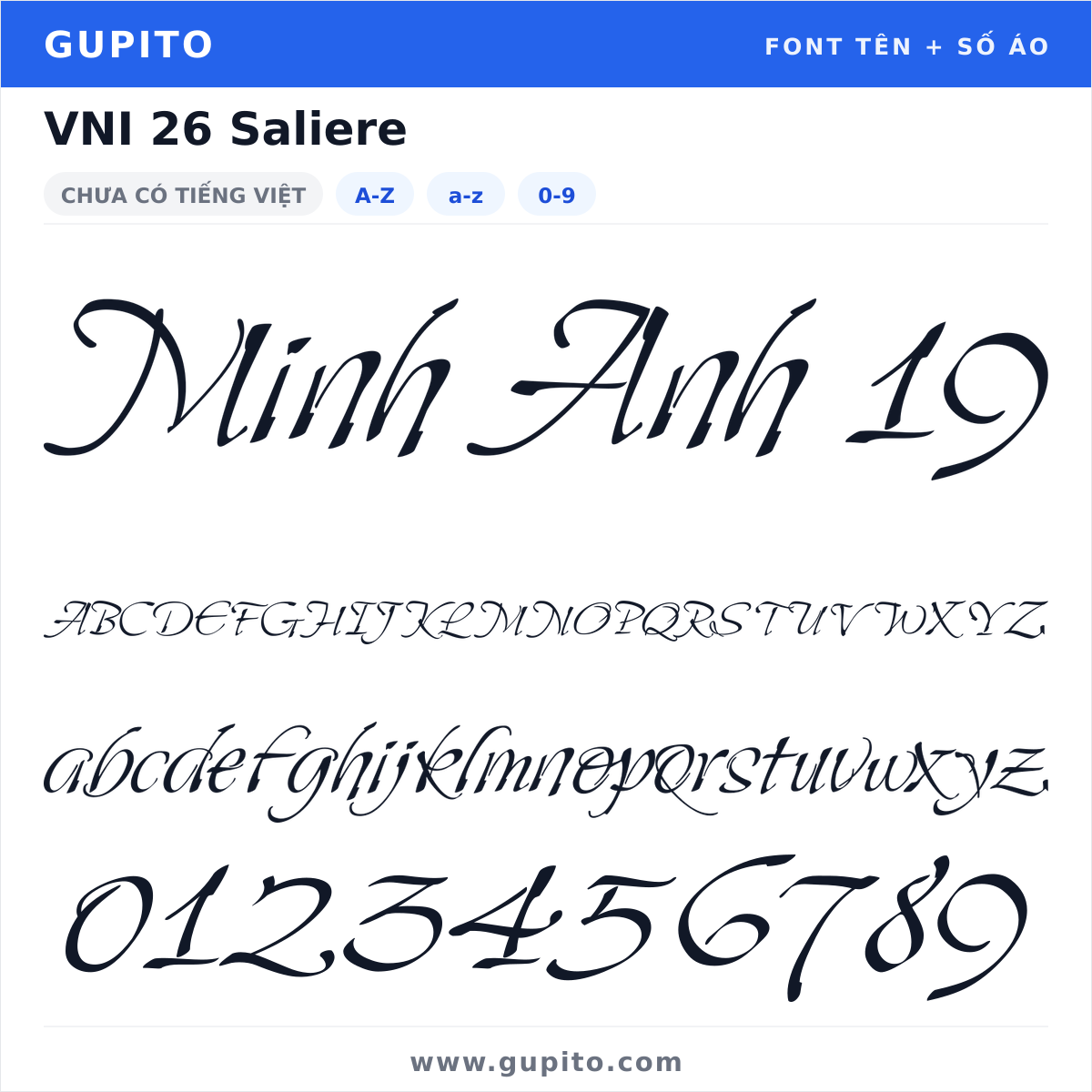
VNI 26 Saliere
VNI 26 Saliere · Font VNI 26 Saliere in tên áo, số áo, chữ ký · chữ ký mềm mại
Font VNI 26 Saliere với nét chữ mềm mại, uyển chuyển, phù hợp in tên áo, số áo, logo, quà tặng. Có bảng số 0-9. Bộ chữ VNI 26 Saliere dùng để in chuyển nhiệt lên áo đấu, áo lớp, áo nhóm và đồ thể thao theo yêu cầu. Kiểu dáng: chữ ký mềm mại. Font dùng cho chữ không dấu và số áo. Có đủ bộ chữ số để in số áo. Từ khoá liên quan: font vni 26 saliere, font chữ ký, font in tên áo, font in số áo, font áo bóng đá, font áo lớp, font quà tặng, font chữ nghệ thuật.